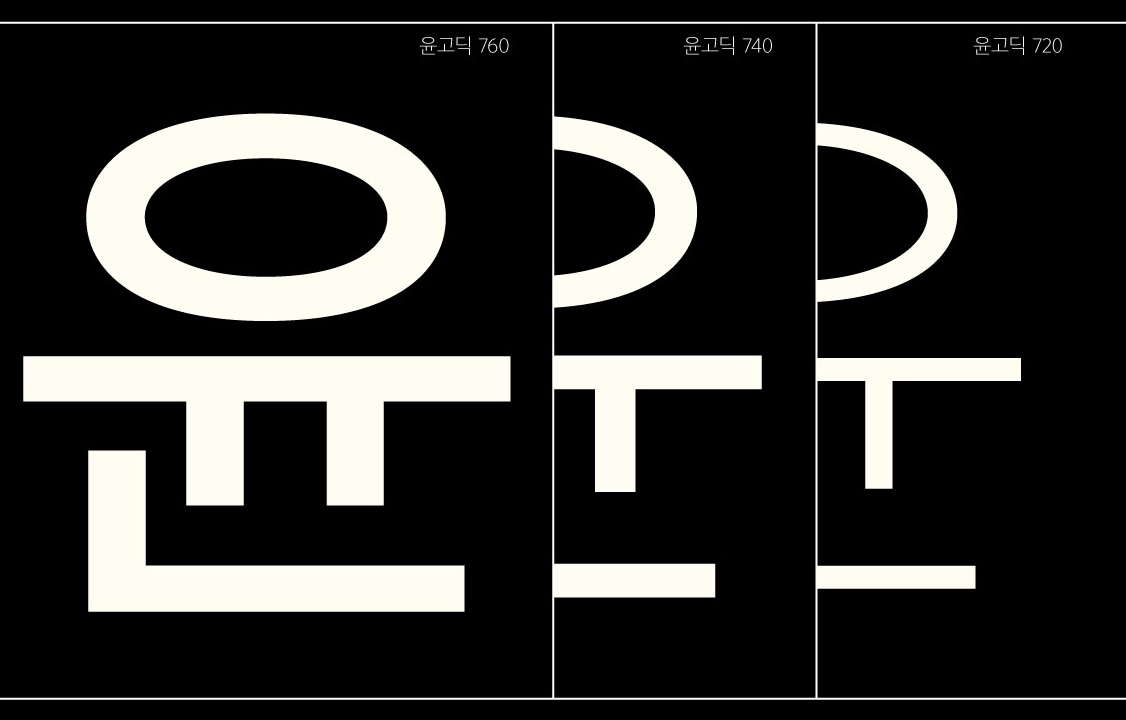
Yoon 윤고딕700
끊임없는 자기 갱신으로 정제에 정제를 거듭해온 윤고딕이 이번에는 온기를 입었습니다. 기존의 모던함을 그대로 지키면서 자간과 속 공간을 오밀조밀 조정해 따뜻한 인상을 강조했어요. 그뿐인가요? 꾸준히 윤고딕을 사랑해주시는 정교한 전문가 여러분을 위해 아홉 명의 글자 대가족을 구성해보았답니다. 편리하게 선택해 사용하세요. 세련된 생김에 따뜻한 배려심까지, 윤고딕에게 부족한 건 도대체 무엇일까요?